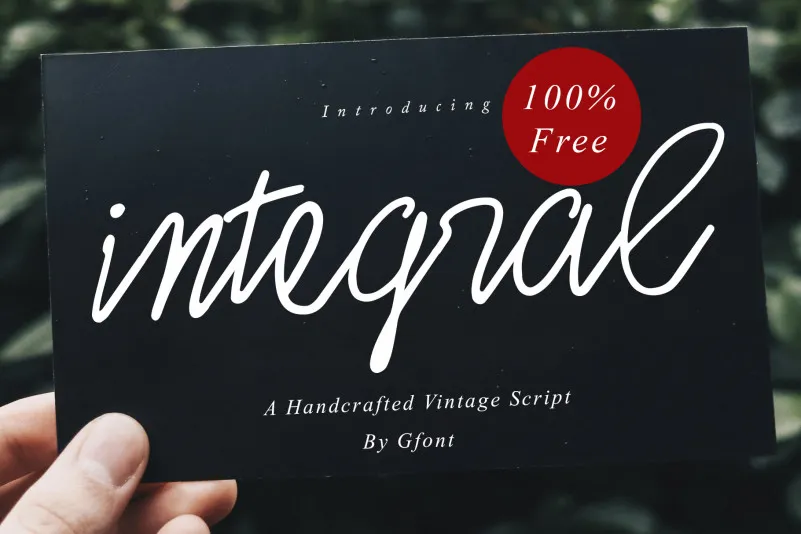
Integral Script Font – Download Grátis
Descubra a beleza do Integral Script Font, uma elegante escrita inspirada na arte da letra feita à mão com caneta. Esta fonte se destaca não apenas por sua graça e delicadeza, mas também pela sua versatilidade moderna, perfeita para projetos variados como logomarcas, rótulos de produto, embalagens, convites sociais, cabeçalhos e anúncios. A Integral Script é uma escolha inconfundível para quem busca desenhar designs únicos e versáteis, capazes de alcançar um público mais amplo. Seja você um designer profissional ou iniciante, esta fonte está aqui para complementar sua paleta de recursos gráficos.
Designer: Gfont